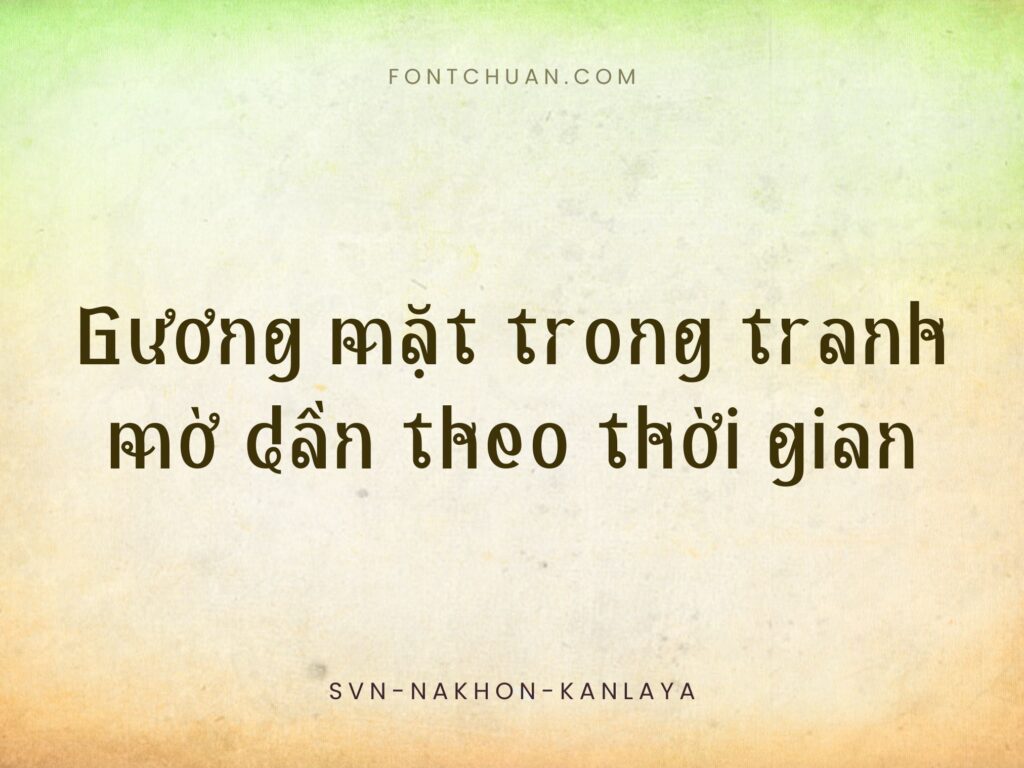
Font SVN Nakhon Kanlaya Việt Hóa
Tác giả Font: Ahmad Ramzi Fahruddin
Font SVN Nakhon Kanlaya là phiên bản Việt hóa của kiểu chữ Nakhon Kanlaya, được thực hiện bởi STYLEno.1 Fonts. Nakhon Kanlaya là một kiểu chữ hiển thị độc đáo, lấy cảm hứng từ các ký tự trong chữ viết Thái Lan, được thiết kế bởi Ahmad Ramzi Fahruddin. Font này nổi bật với các đường nét cong và hình dạng tròn, mang đậm nét văn hóa Thái, tạo nên sự khác biệt và ấn tượng trong thiết kế. Với phong cách độc đáo và đường nét mềm mại, SVN Nakhon Kanlaya cũng có thể được sử dụng như một Font chữ Halloween, mang lại cảm giác mới lạ, vui tươi nhưng vẫn bí ẩn cho các ấn phẩm chủ đề lễ hội. Nakhon Kanlaya bao gồm đầy đủ các ký tự chữ hoa, chữ thường, chữ số và dấu câu, hỗ trợ đa ngôn ngữ. Font này phù hợp cho nhiều mục đích sử dụng khác nhau như thiết kế bao bì, nhãn dán, áp phích, quảng cáo và các ấn phẩm truyền thông.
SVN Nakhon Kanlaya lý tưởng cho các dự án thiết kế yêu cầu sự độc đáo và mang đậm nét văn hóa Đông Nam Á, như thiết kế logo, tiêu đề, bao bì sản phẩm và các ấn phẩm truyền thông. Các ngành nghề như quảng cáo, ẩm thực và giáo dục có thể tận dụng font này để tạo điểm nhấn trong thiết kế. Ngoài ra, font cũng thích hợp cho các sự kiện như Halloween, Tết, Lễ hội và các dịp đặc biệt khác.